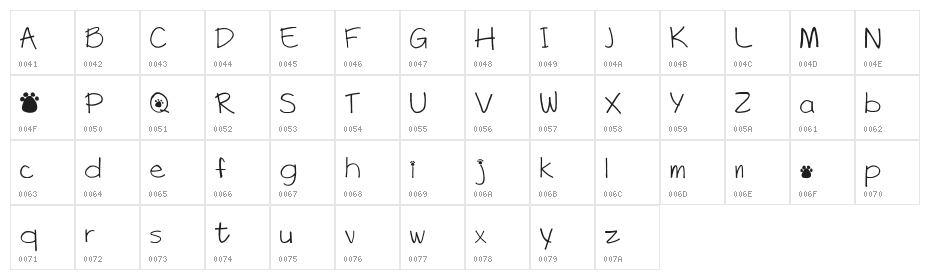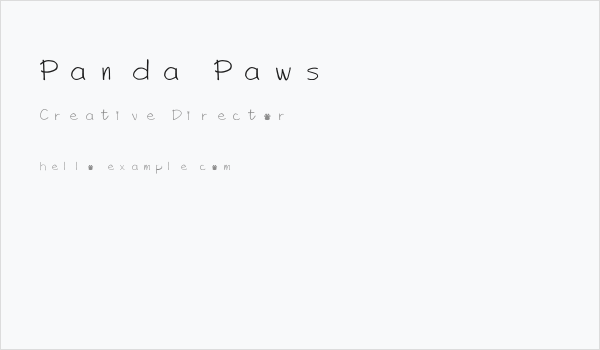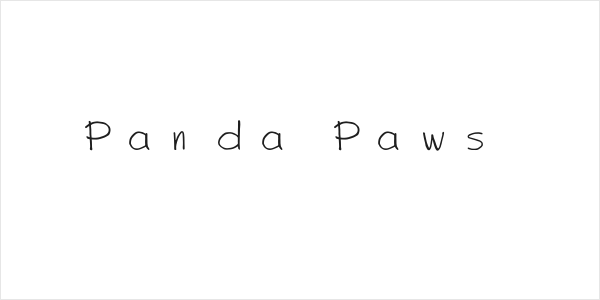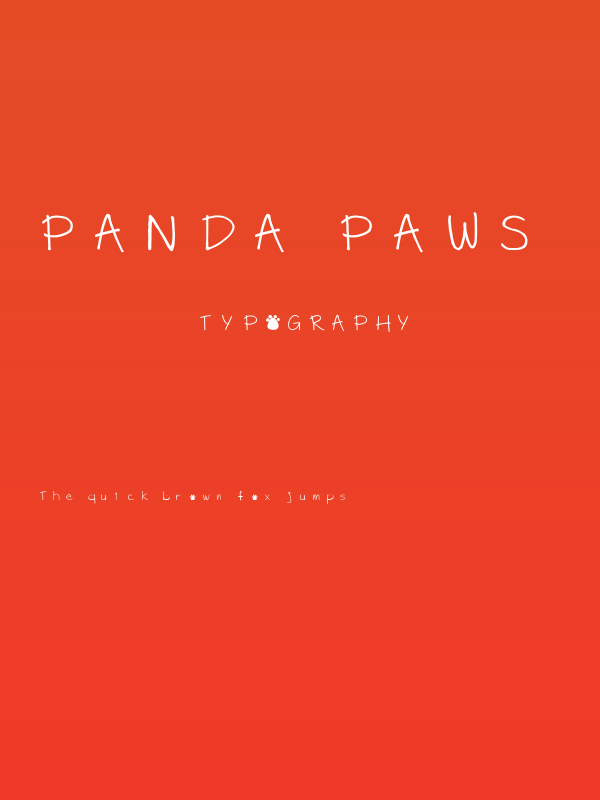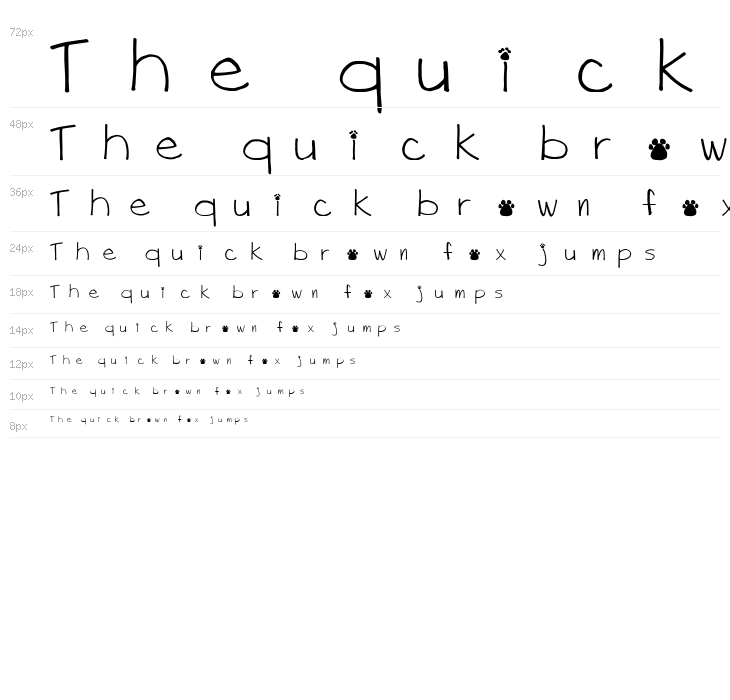
Panda Paws Font
| Anwendungsfall | Logos, Invitations, Children's materials |
| Vorgeschlagene Projekte | Ideal for children's books, playful branding, pet-related products, and casual invitations. |